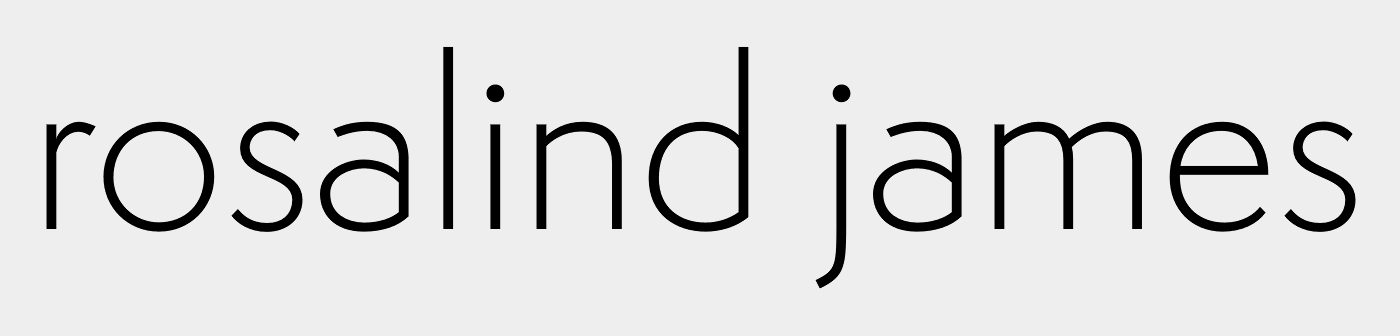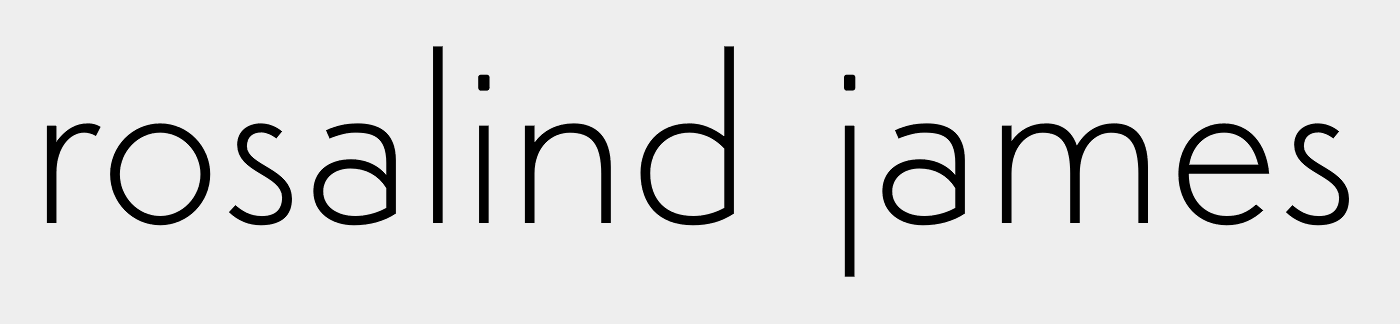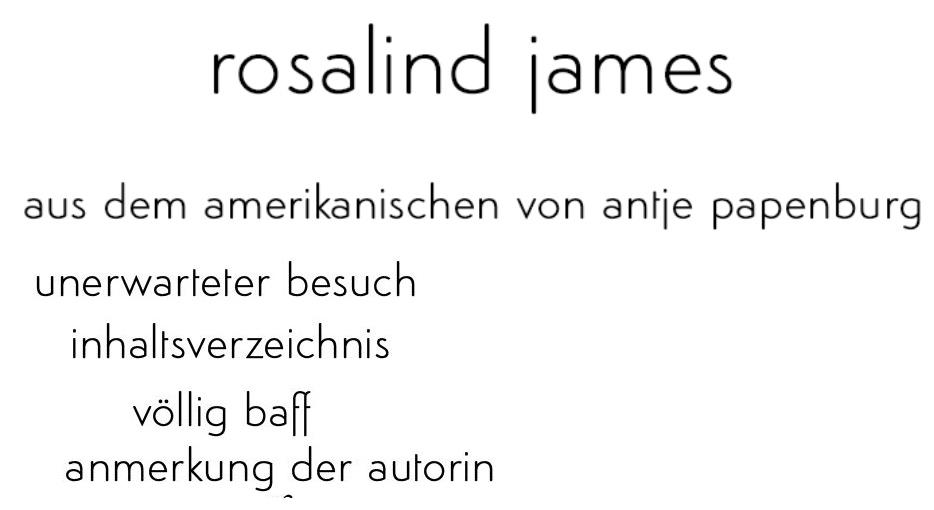
Suche Schrift eines Rosalind James Buches
Ich suche diese Schrift aus der (Bücher-)Reihe von Rosalind James "Neuseelandreihe".
Es sind u.a. die Kapitelüberschriften in zB dem Buch "Wiedersehen in Neuseeland"
Hallo @Amaliah, die Simplo von Durotype (Ben Blom, 2011) ist nicht kostenlos, sollte aber passen.
Eine etwas andere Interpretation der Original-»Semplicità« von Alessandro Butti (1930) bietet Canada Type als Semplicita Pro an (Patrick Griffin, Bill Troop, auch 2011). Vielleicht gefällt dir diese ja auch.
Die Canada-Type-Schriften sind in der Regel sehr hochwertig; mit Durotype habe ich noch keine Erfahrungen gemacht.
ich habe da ein schwaches Erhellen in meinen Synapsen. Die beiden erwähnten Schriften habe ich hier dokumentiert ...  Von der Semplicita liegt hier die Info von Identifont rum, Ein GIF-Bildchen und eine Textzusammenfassung:
Wird in Italien ans Schrift der Faschisten gesehen.